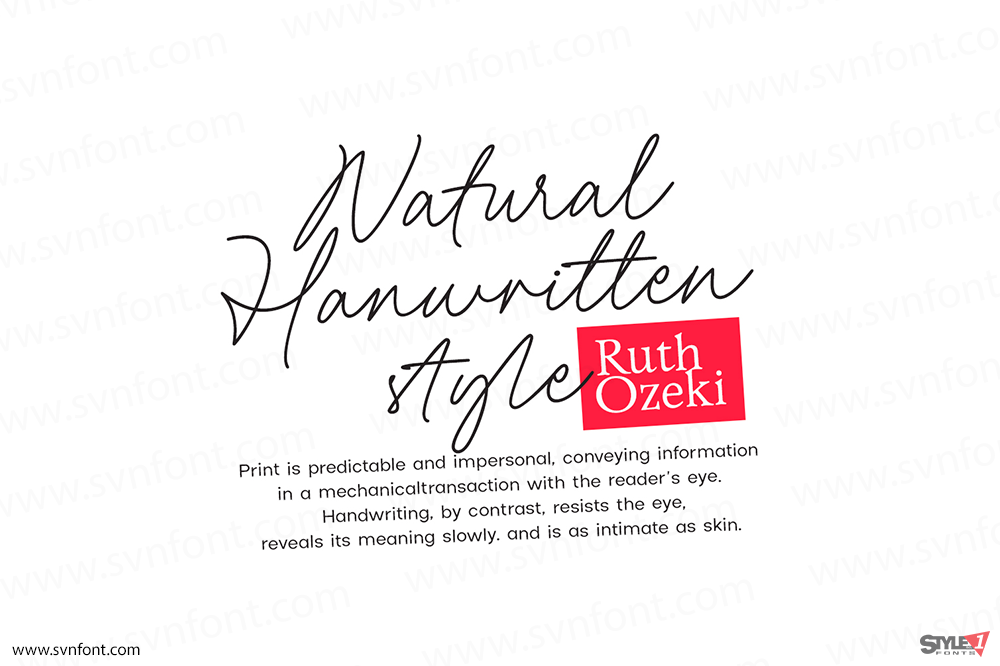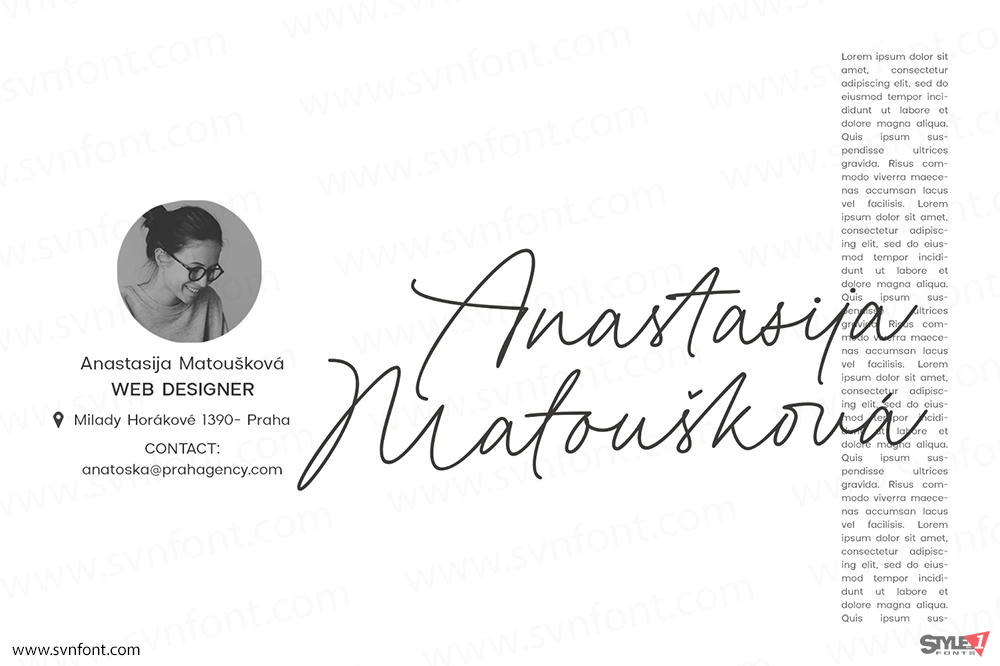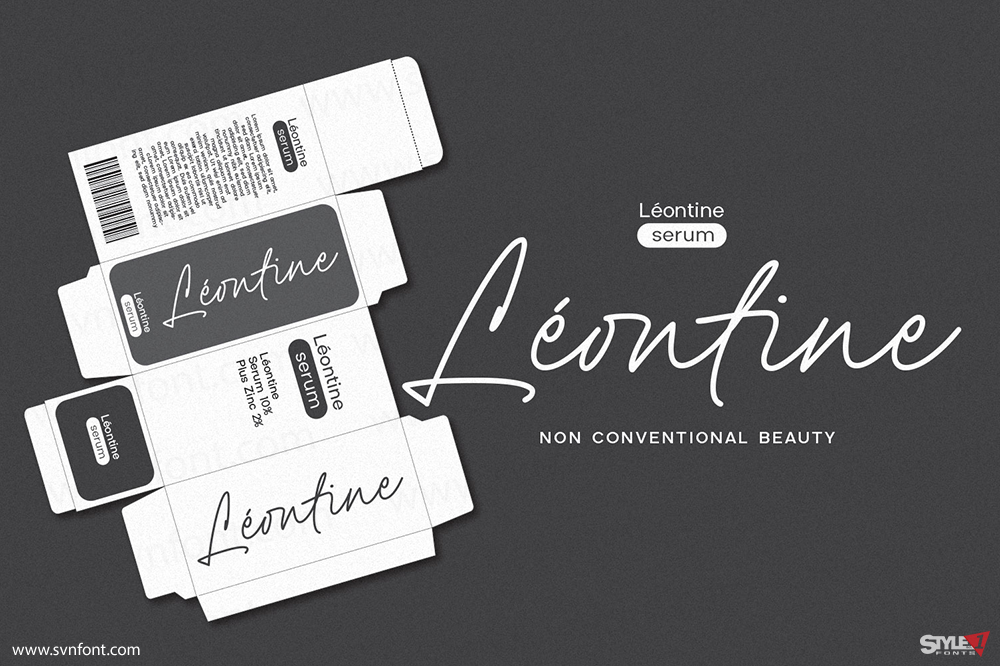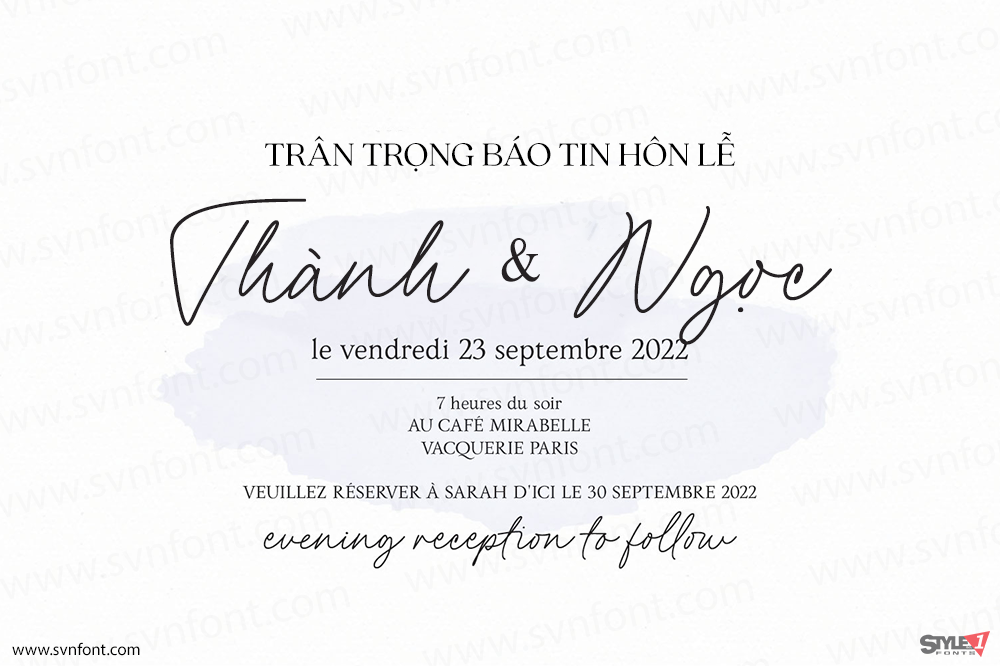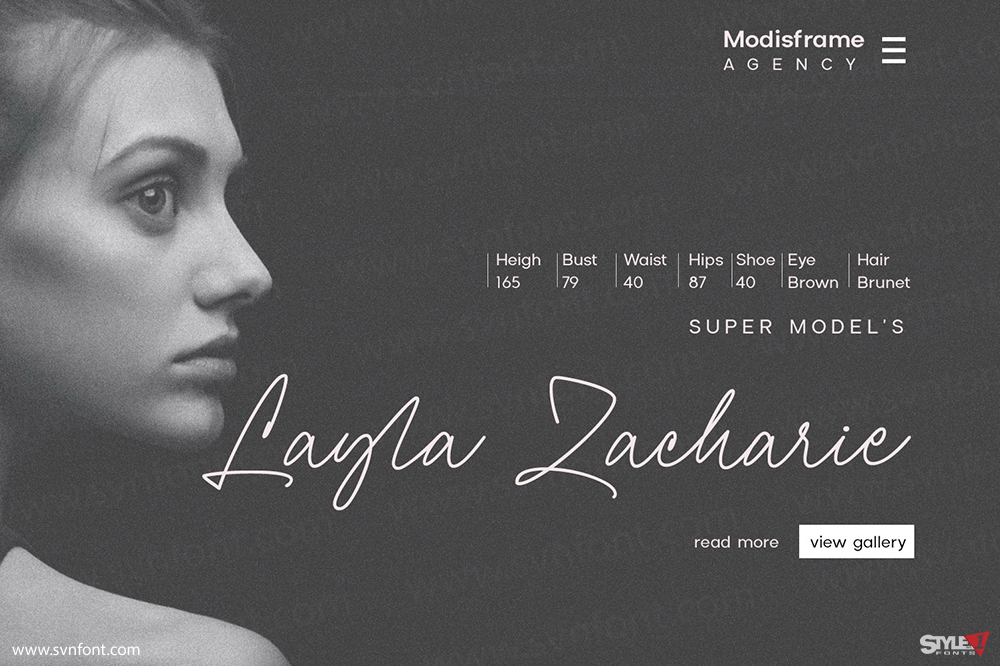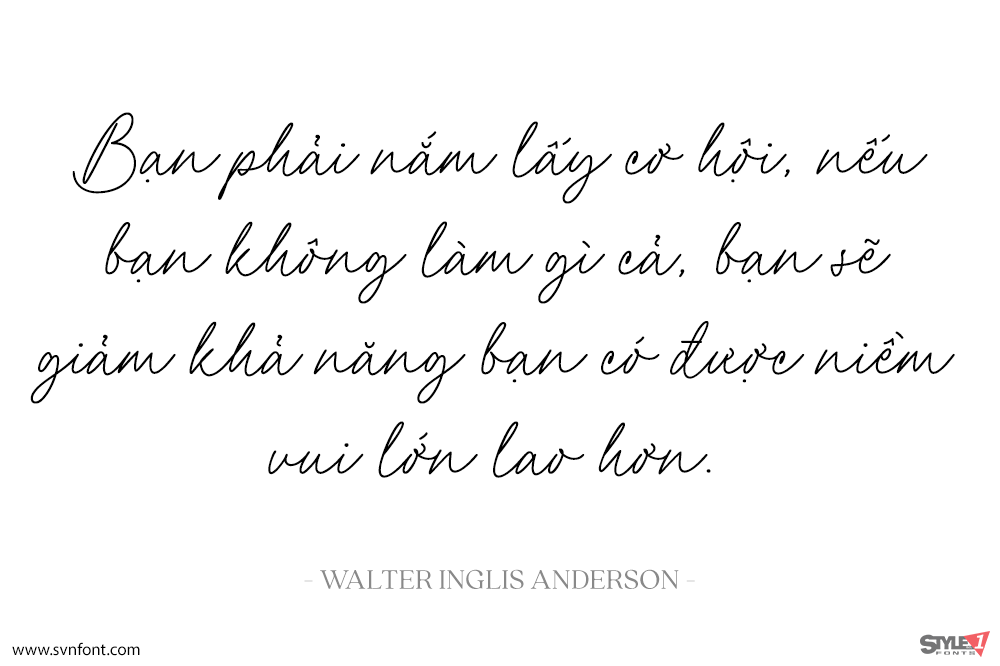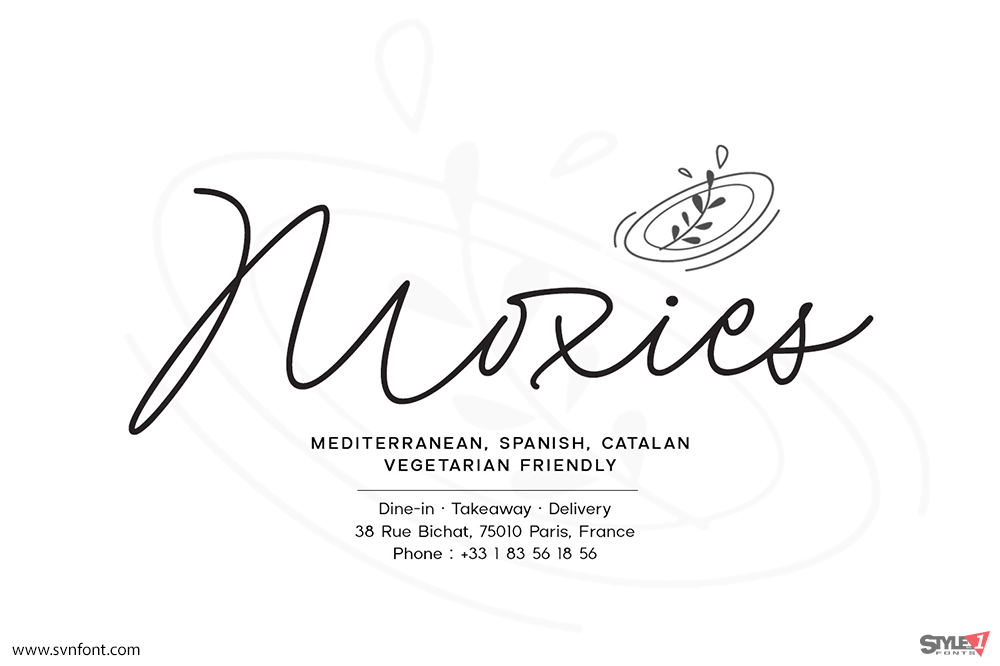
Modisframe là một font chữ ký hiện đại đầy phong cách với nét bút mono-line nhẹ nhàng. Font chữ viết tay này có 100 nét nối (ligature) hỗ trợ đa ngôn ngữ. Modisframe mang đặc tính của sự ngẫu hứng và quyết đoán. Nó sẽ trông tuyệt vời cho chữ ký điện tử, logo, trích dẫn, thiệp chúc mừng, nhãn mác, bao bì, lớp phủ trên mạng xã hội, các bản in, quảng cáo hoặc tạo thiệp mời đám cưới thanh lịch và nhiều hơn nữa.